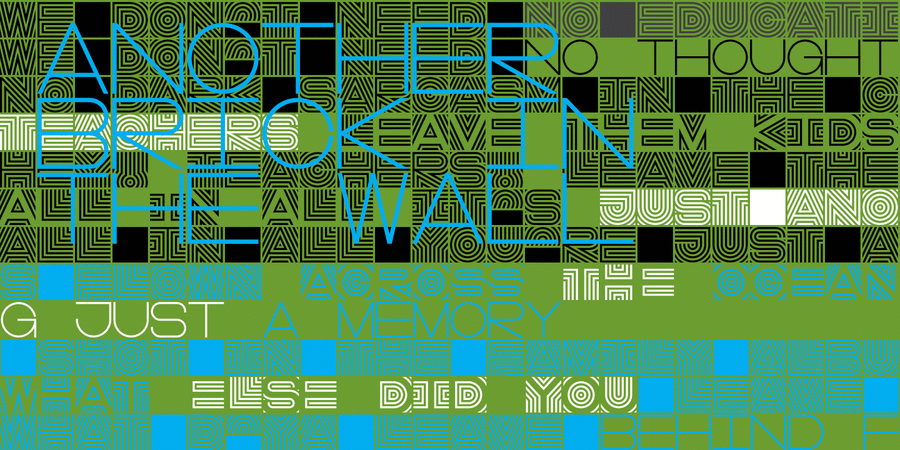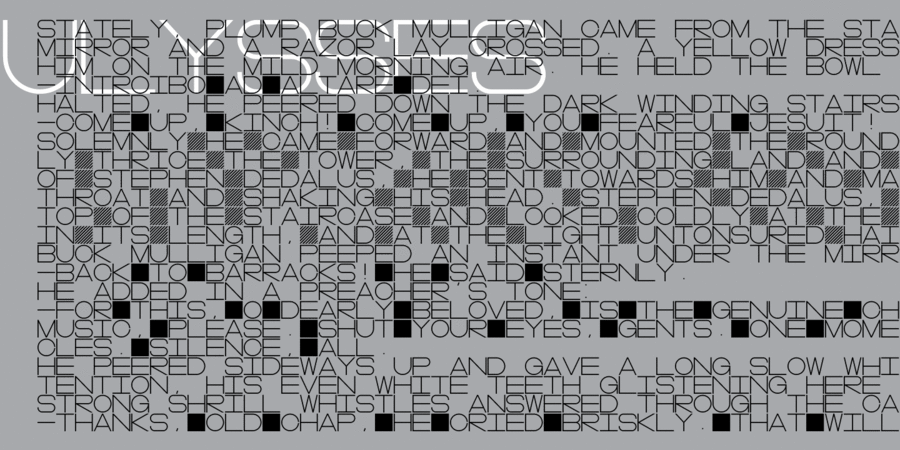
Акцидентна багатошарова гарнітура в стилі оп-арт з підтримкою латиниці, кирилиці та грецької. DR Lineart отримав нагороду The Best Of Ukrainian Design in Typestyle and typography 2016. Шрифт розробив Дмитро Растворцев у 2016-2017 році.
Асоціації з сімейством шрифтів DR LineartОсобистість і характер гарнітури:
пульсуючий, оригінальний, виразний, якісний, молодіжний, дзвінкий, сучасний, міський, клубний, музичний, прозорий, точний, яскравий, рівний, ритмічний, привабливий, кислотний, експериментальний, дивний, електронний, автоматичний, машинний, сталевий, комп'ютерний, гострий, різкий, чіткий, жорсткий, колючий, квадратний, архітектурний, урбаністичний, техногенний, матричний, індустріальний, мерехтливий, психоделічний, нічний, важкий, тонкий, дротяний, креслярський, інженерний
розваги, телебачення, шоу, музика, нічний клуб, дизайн, гра, Місто, клуб, атракціон, електроніка, автоматика, залізо, анімація, IT, робот, фантастика, архітектура, архітектор, андроїд, конструктор, айтішник, техніка, урбаністика, танець, головокрутка, прилад, інструмент, креслення, інженер, будівництво, завод Гарнітура має ознаки стилів: